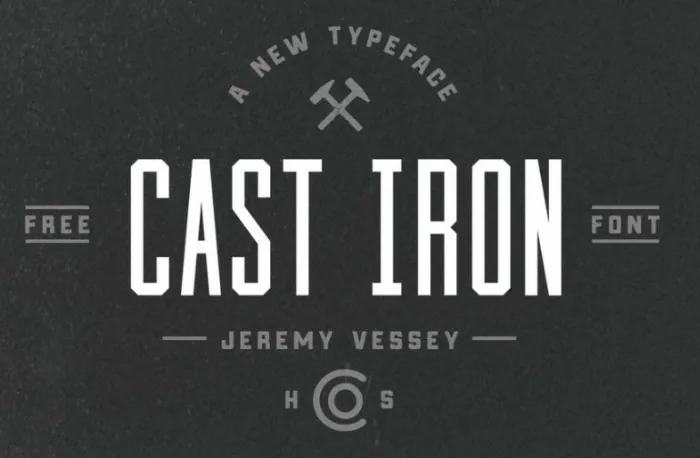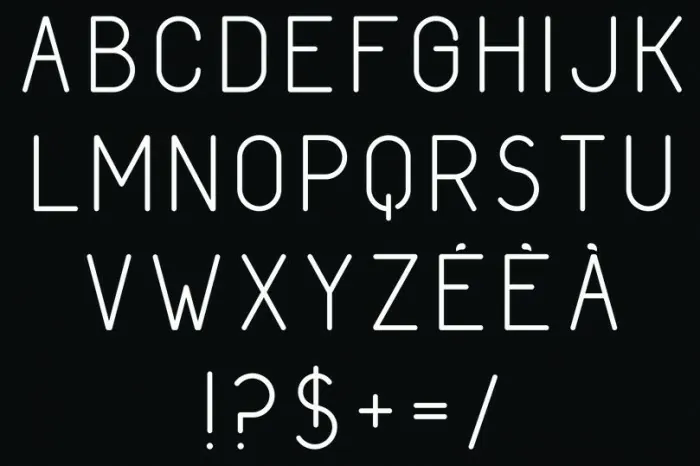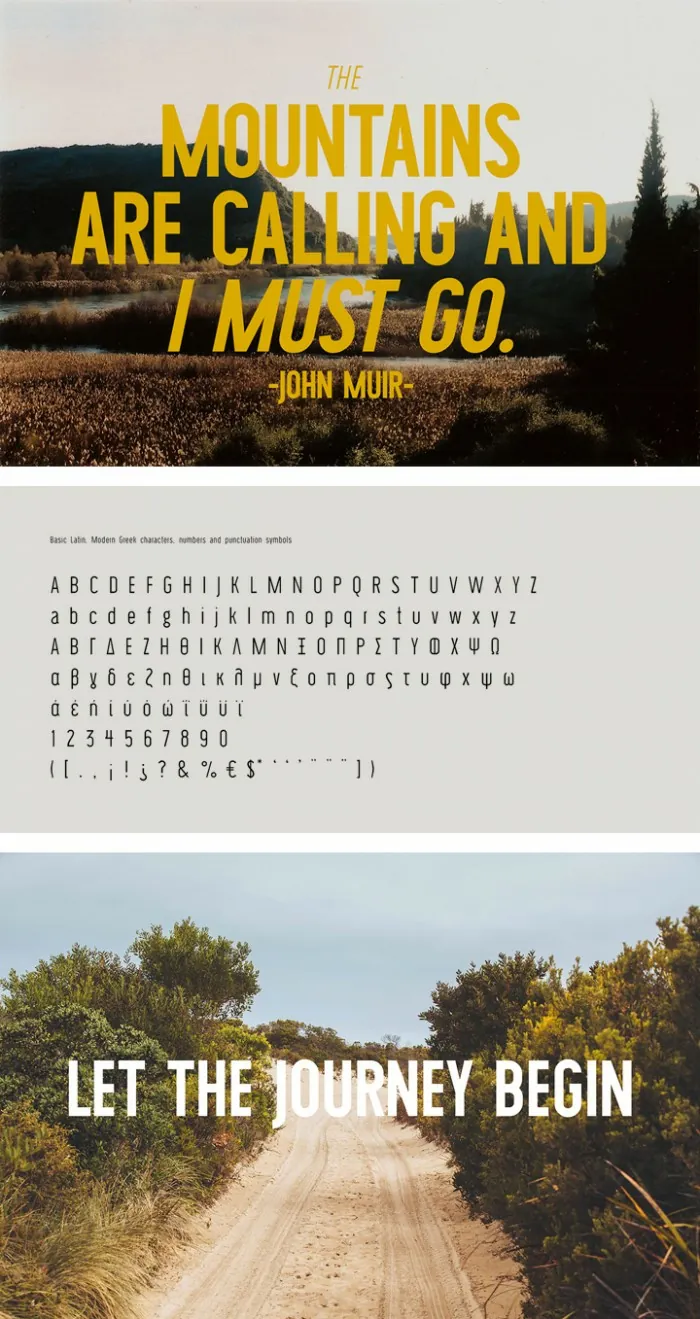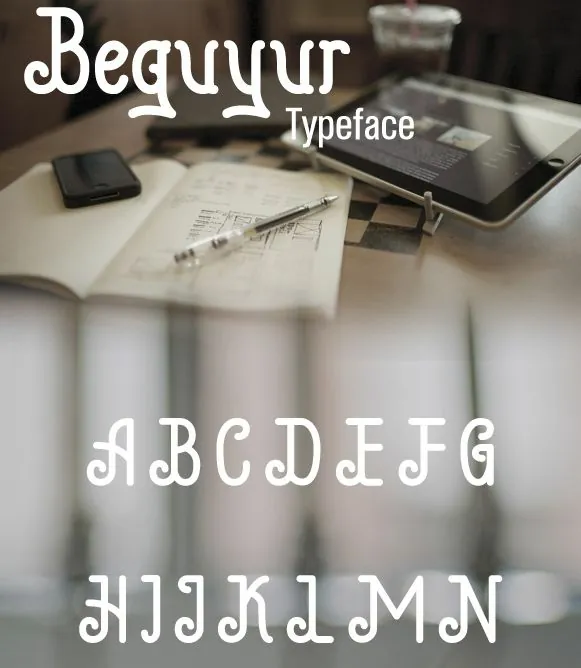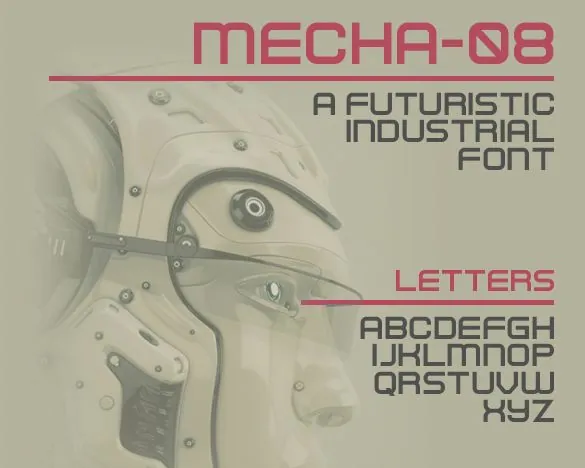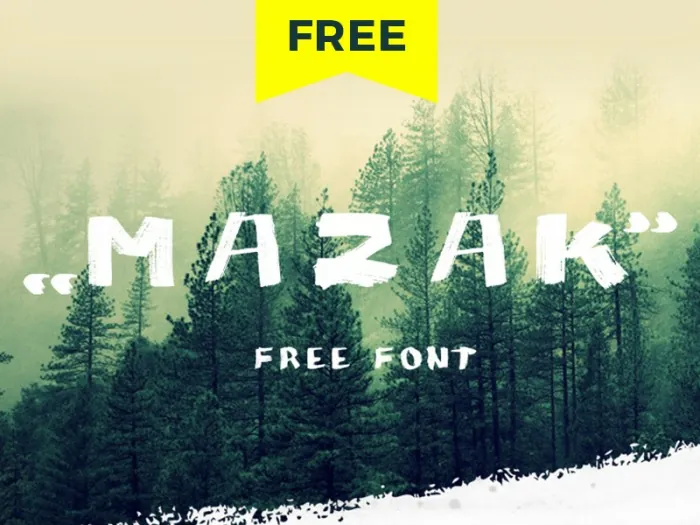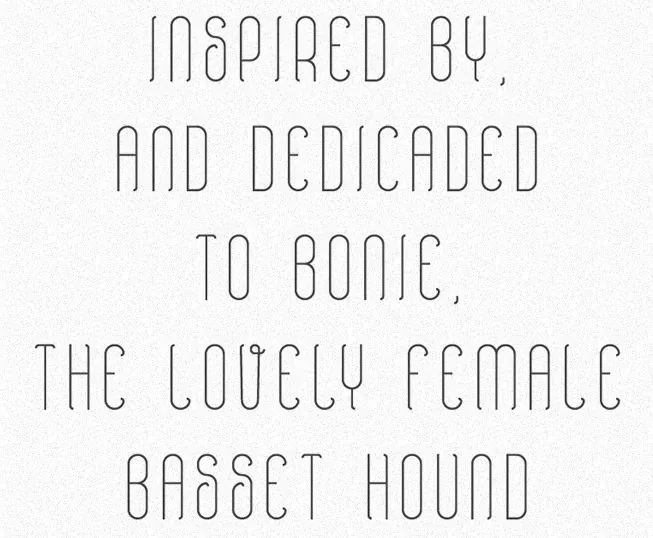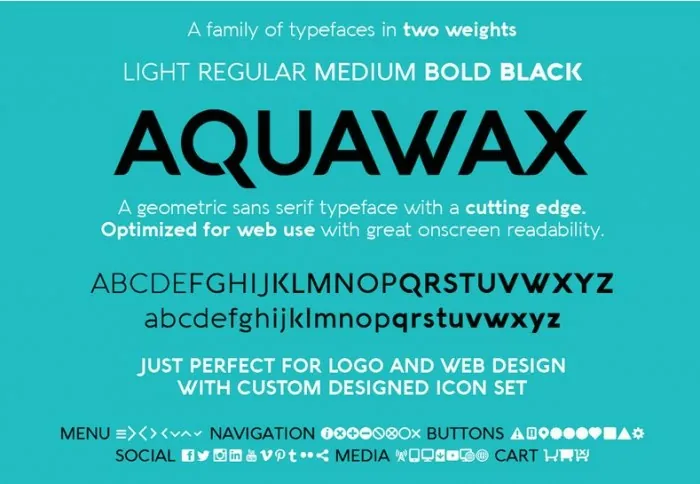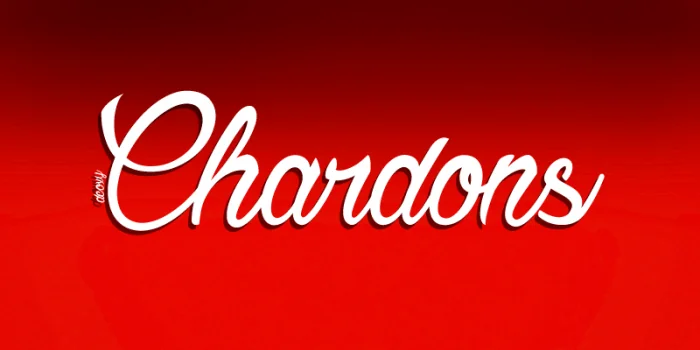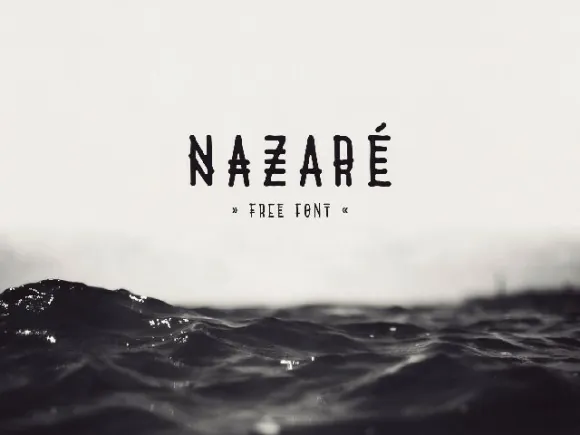
En el artículo de hoy te invito a ver una colección de tipografías de calidad gratis para diseñadores web y gráficos.
Son fuentes no muy vistas, que seguramente te ayudarán a dar el toque que necesita tu diseño.
Free Condensed
Quest
Aquawax Font
Es una tipografía de la familia sans serif. Esta fuente recuerda a lo digital, por sus formas redondeadas y sus ángulos. Usa el alfabeto latino, con amplio rango de acentos.
Chardons
Nazaré free font
Fuente gratuita en mayúsculas inspirada en un pueblo de Portugal.
Mylodon Font
Curely
Es una fuente decorativa hecha a mano.
Wask fuente gratuita
Esta tipografía es condensend, sans serif. Incluye dos grosores distintos, además de la cursiva. Es ideal para títulos, posters,…
Beguyur Typeface
Mecha 08
Mazak
Bonnie
Es una tipografía muy elegante que viene incluida con acentos. La podrás utilizar gratis para proyectos personales y profesionales.